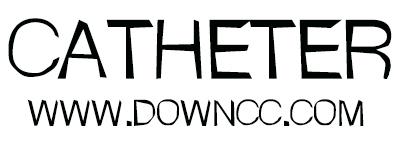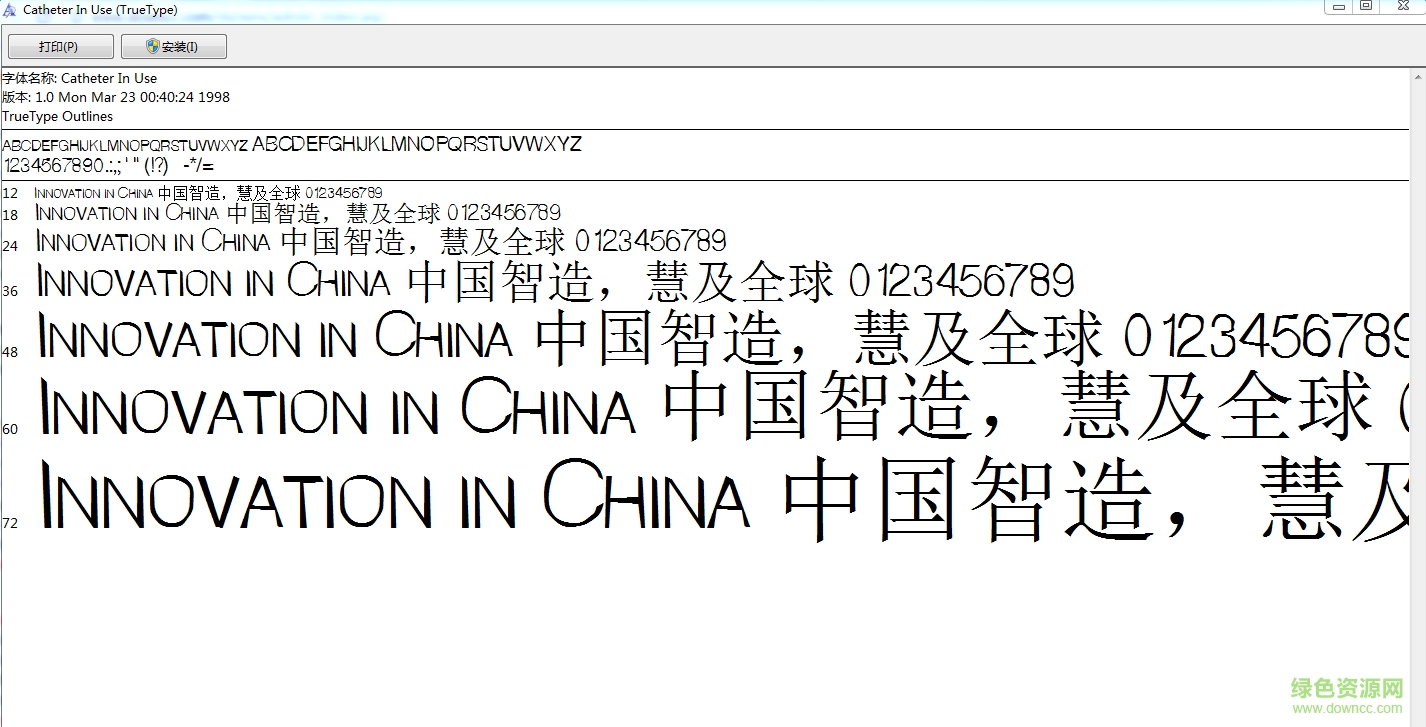
catheter字體是一款免費(fèi)的英文字體軟件,全新英文字體給人非常舒服的感覺(jué),菱角有種被去除的感覺(jué),深受廣大書(shū)法家的喜愛(ài)!需要的用戶(hù)歡迎到綠色資源網(wǎng)下載體驗(yàn)!
Catheter是一款英文字體,字體效果比較圓滑,喜歡英文字體的朋友可以下載使用看看效果如何。